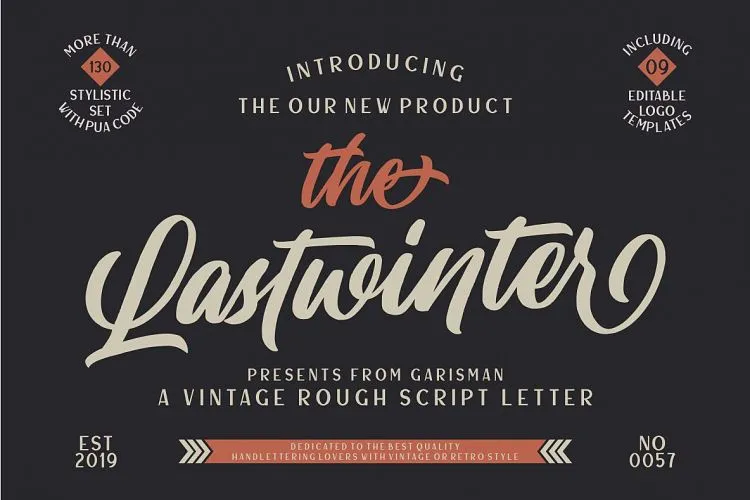
Lastwinter Script Font – Fonte Grátis
Lastwinter Script Font
A nova fonte ‘Lastwinter Script Font’ é uma exuberante cópia de letra script que captura a essência única e elegante dos desenhos à mão. Desenvolvida pelos mestres do tipo de texto 0001themes, ela incorpora traços distintivos para criar um visual natural e envolvente, como se fossem escritos ao vivo por alguém com experiência. Este é um fonte perfeitamente adaptável a uma variedade de mídias, desde embalagens até desenhos de camisetas, logotipos e publicações impressas. Além disso, ‘Lastwinter Script Font’ apresenta 8 conjuntos de estilo únicos para o alfabeto minúsculo e alternativas variadas para as letras maiusculas. Esta fonte é perfeita para designers que desejam adicionar um toque único aos seus projetos sem sair do conforto daquilo que já conhecem. Com sua origem nas linhas suaves das mãos humanas, ‘Lastwinter Script Font’ oferece uma solução ideal tanto para designers de logotipos quanto para aqueles trabalhando em arte gráfica. Com o seu uso em materiais variados como embalagens e posters, a ‘Lastwinter Script Font’ cria um visual impactante que faz do texto uma parte essencial da sua mensagem. Sem dúvida, este é um recurso fonte que todos os criadores de design devem ter na sua coleção.